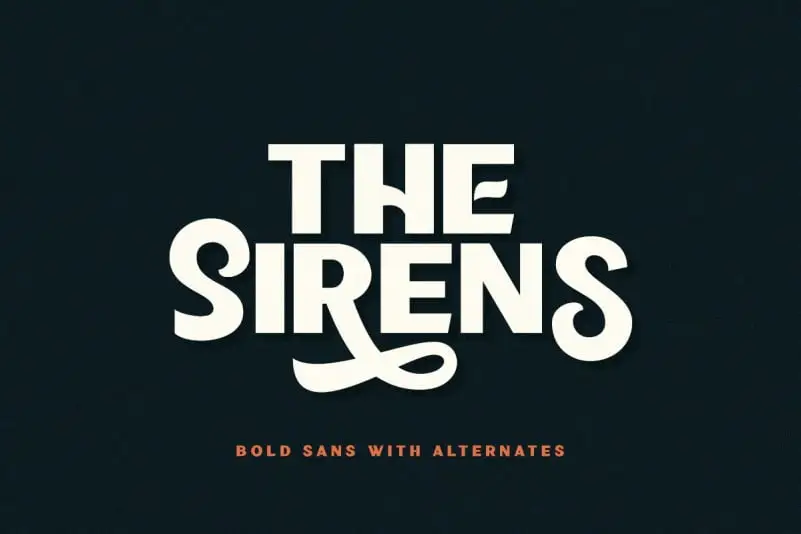
A Sirens Sans Serif é uma fonte casual e moderna que oferece uma experiência única para quem busca uma linguagem mais limpa e simplificada sem perder a personalidade. Este tipo de tipo foi criado por Saridezra, está disponível no 99designs e sua maior característica especial é a inclusão de alternativas em cada letra minúscula. Cada alfabético vem com três tipos diferentes de alternativas! Esta fonte se encaixa em qualquer projeto, especialmente ideal para aplicações como headlines. Você pode usá-la para subtítulos, logomarcas, citações ou até mesmo combinar com outras fontes. Mas o que realmente torna a Sirens Sans Serif única é seu suporte multi-língue e sua codificação PUA já incluída, permitindo um uso fluido em projetos internacionais. Tudo isso em uma linguagem que se mantém claramente moderna e casual, sem perder o charme de uma fonte com alternativas personalizadas. Esta font é a escolha perfeita para qualquer projeto que busca estética simples e sofisticada, oferecendo aos designers mais opções para criar um design único e impactante.